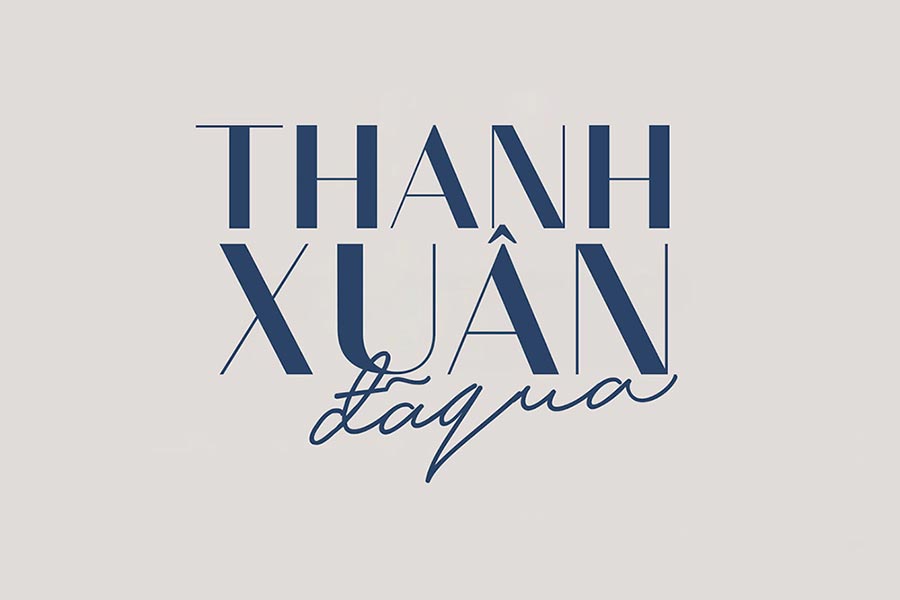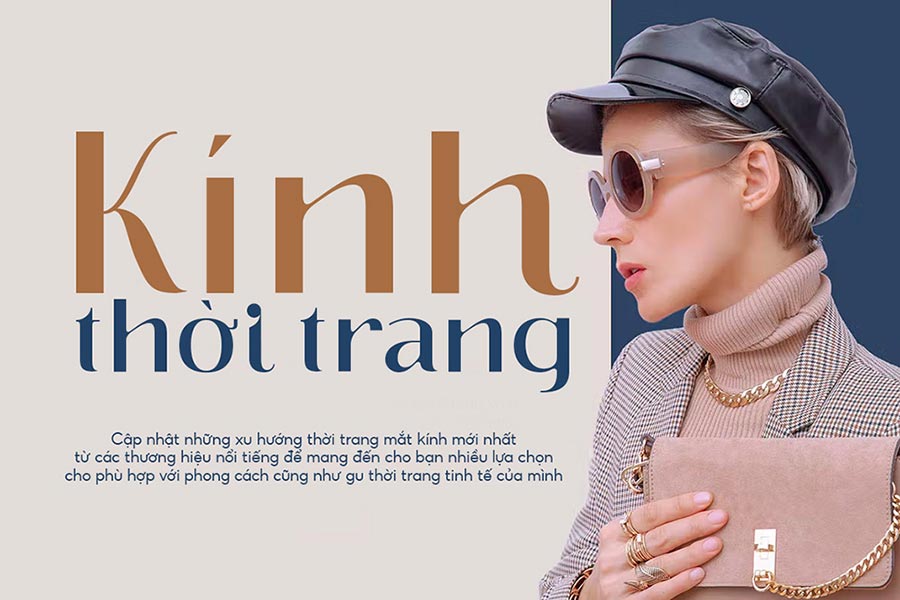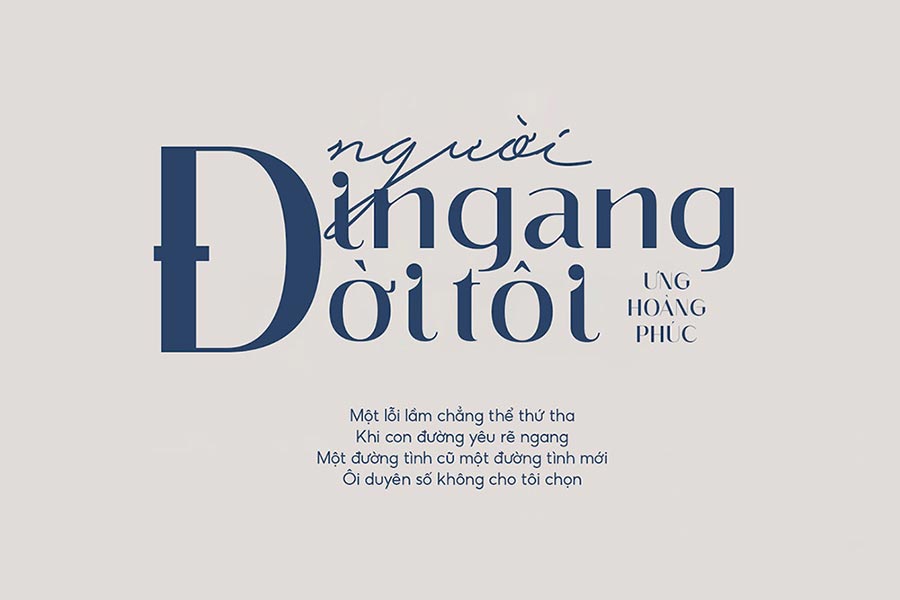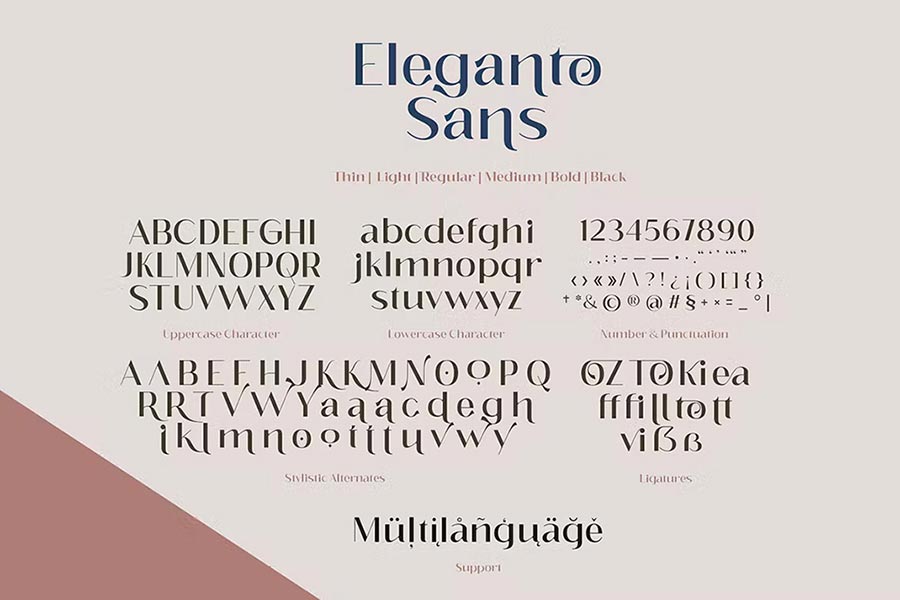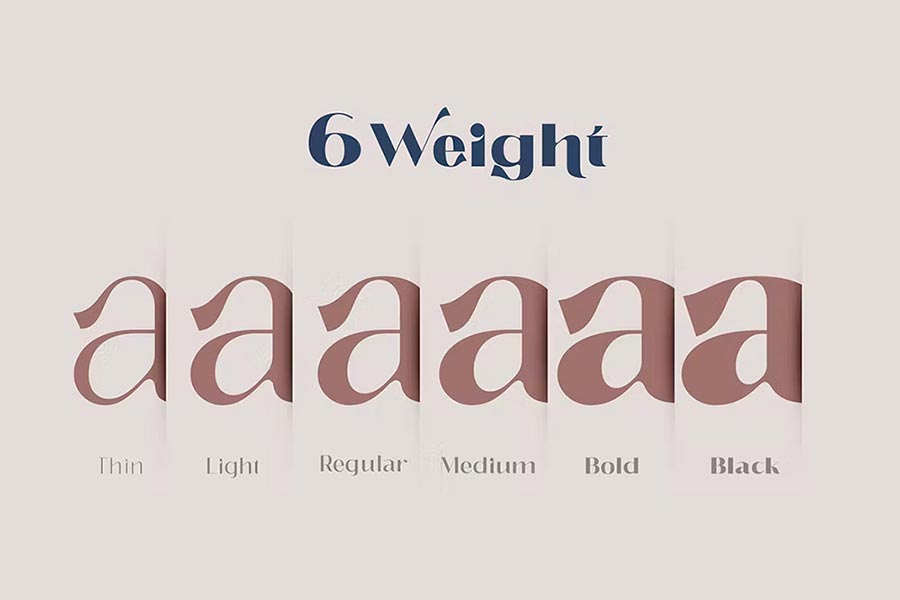
Chia Sẻ Miễn Phí Font Việt Hóa - Eleganto Cực Đẹp Hiện Đại Hợp Thời Trang
Tại Sao Eleganto Là Font Chữ Đáng Sử Dụng?
1. Thiết Kế Hiện Đại, Phong Cách Tối Giản
Eleganto được thiết kế với phong cách hiện đại, tập trung vào các đường nét mảnh, gọn gàng và tinh tế. Font chữ này phù hợp với nhiều lĩnh vực khác nhau, từ thời trang, mỹ phẩm đến các sản phẩm công nghệ. Sự tối giản trong từng chi tiết giúp Eleganto dễ dàng kết hợp với các yếu tố khác trong thiết kế mà không làm mất đi tính thẩm mỹ tổng thể.
2. Hỗ Trợ Tiếng Việt Hoàn Hảo
Một trong những ưu điểm nổi bật của Eleganto là hỗ trợ đầy đủ bộ ký tự tiếng Việt. Điều này giúp bạn không cần lo lắng về việc thiếu ký tự khi sử dụng trong các dự án thiết kế nội dung tiếng Việt. Các dấu câu, ký tự đặc biệt đều được tối ưu hóa để đảm bảo tính đồng nhất và cân đối.
3. Đa Dụng Trong Nhiều Loại Dự Án
Eleganto có thể sử dụng cho nhiều mục đích khác nhau, từ thiết kế logo, banner quảng cáo, poster sự kiện đến các tài liệu in ấn hay giao diện website. Dù bạn đang làm việc trong lĩnh vực nào, font chữ này đều mang đến sự chuyên nghiệp và thu hút.
2. Chất Lượng Đảm Bảo
Font Eleganto được Việt hóa một cách tỉ mỉ, đảm bảo chất lượng từng ký tự. Từ đó, bạn có thể yên tâm sử dụng mà không gặp phải các vấn đề như lỗi hiển thị hay mất cân đối trong thiết kế.